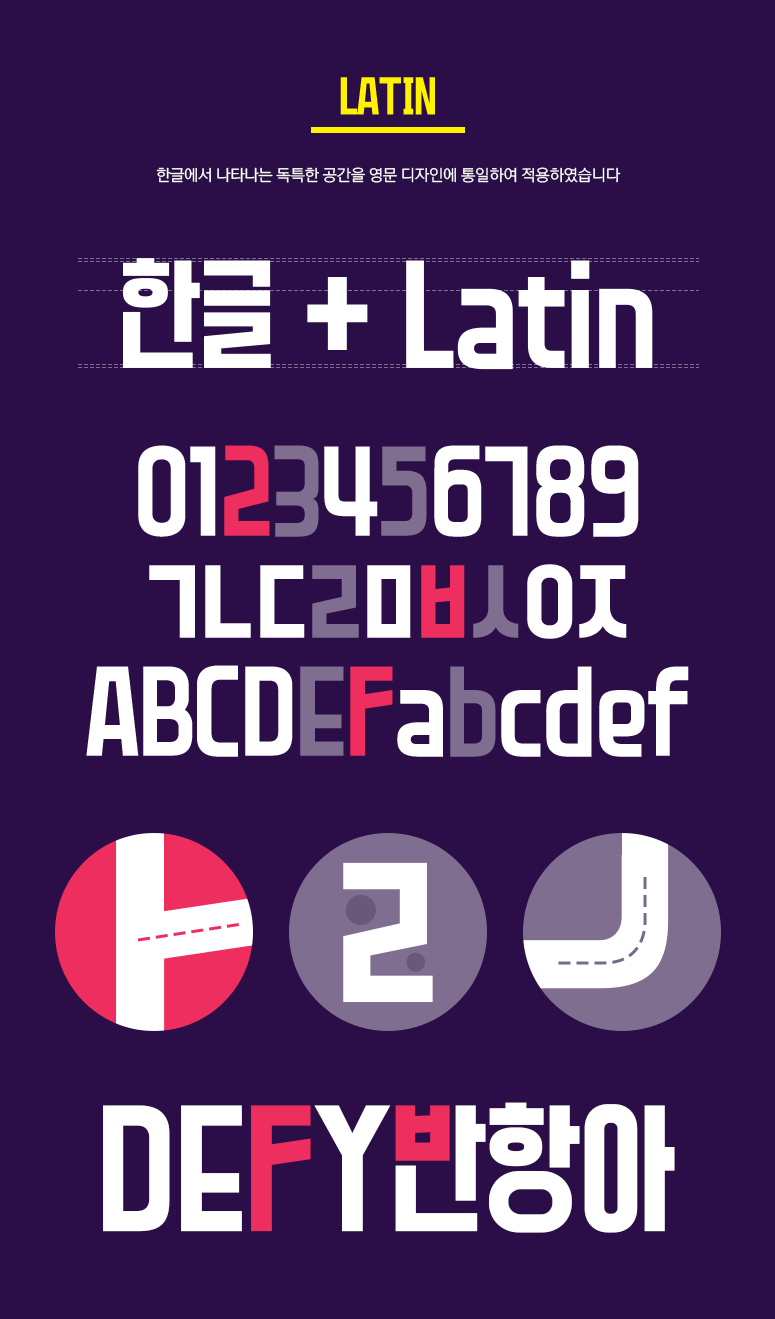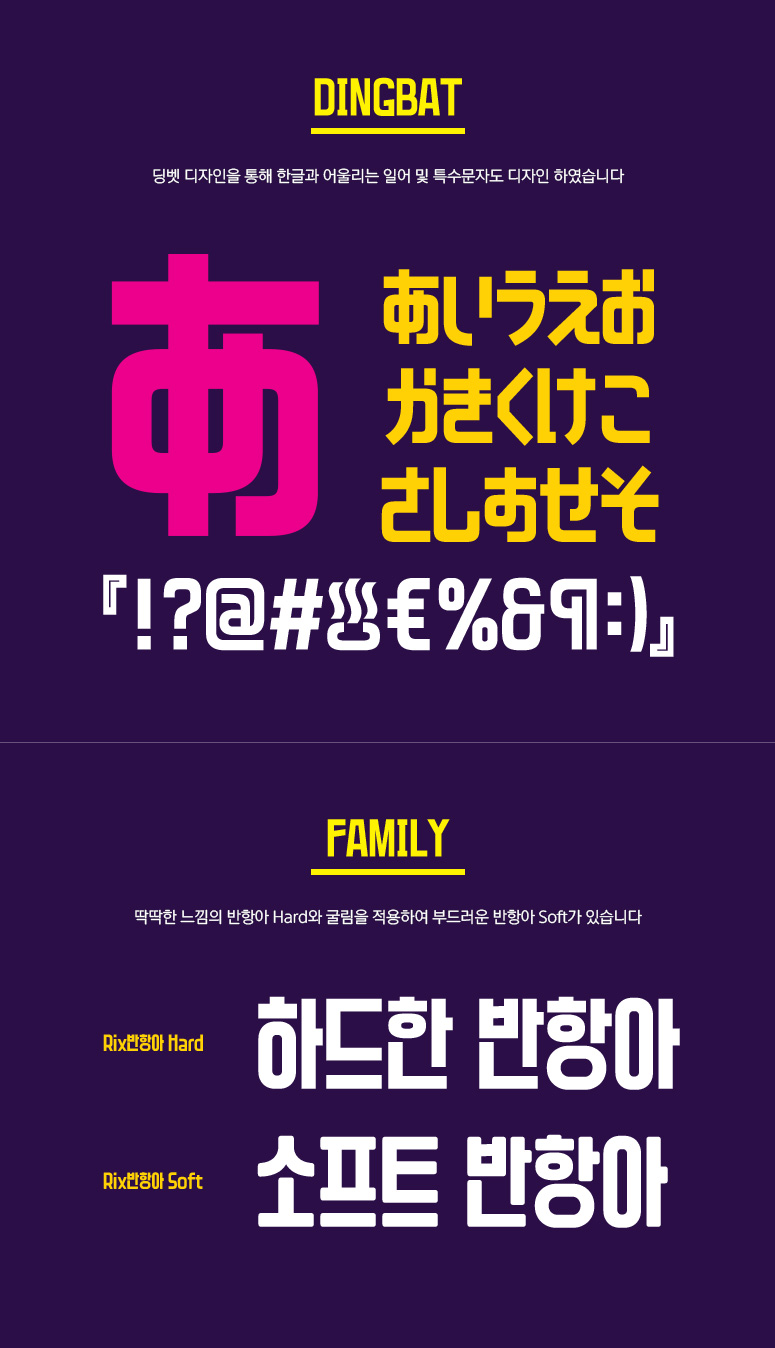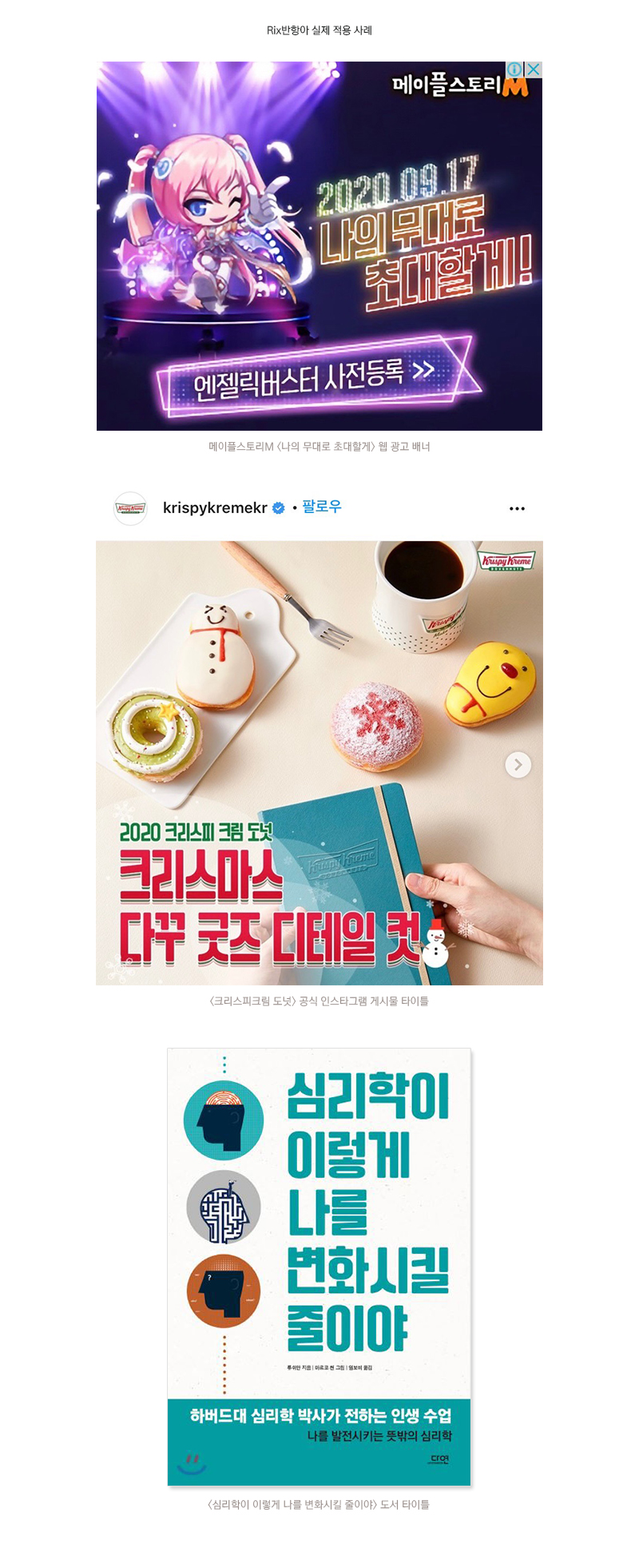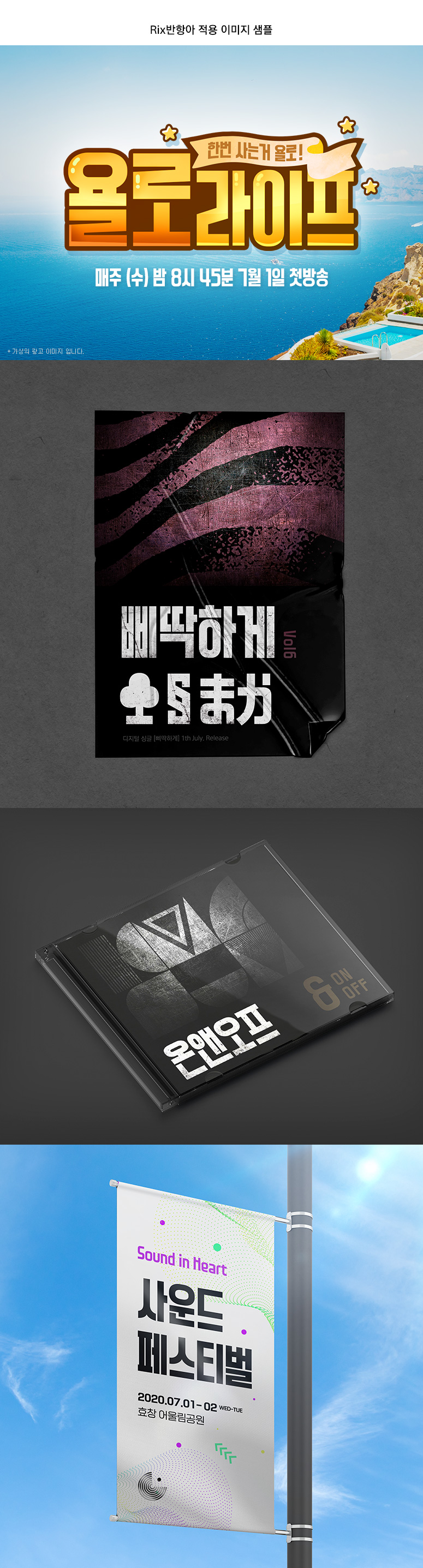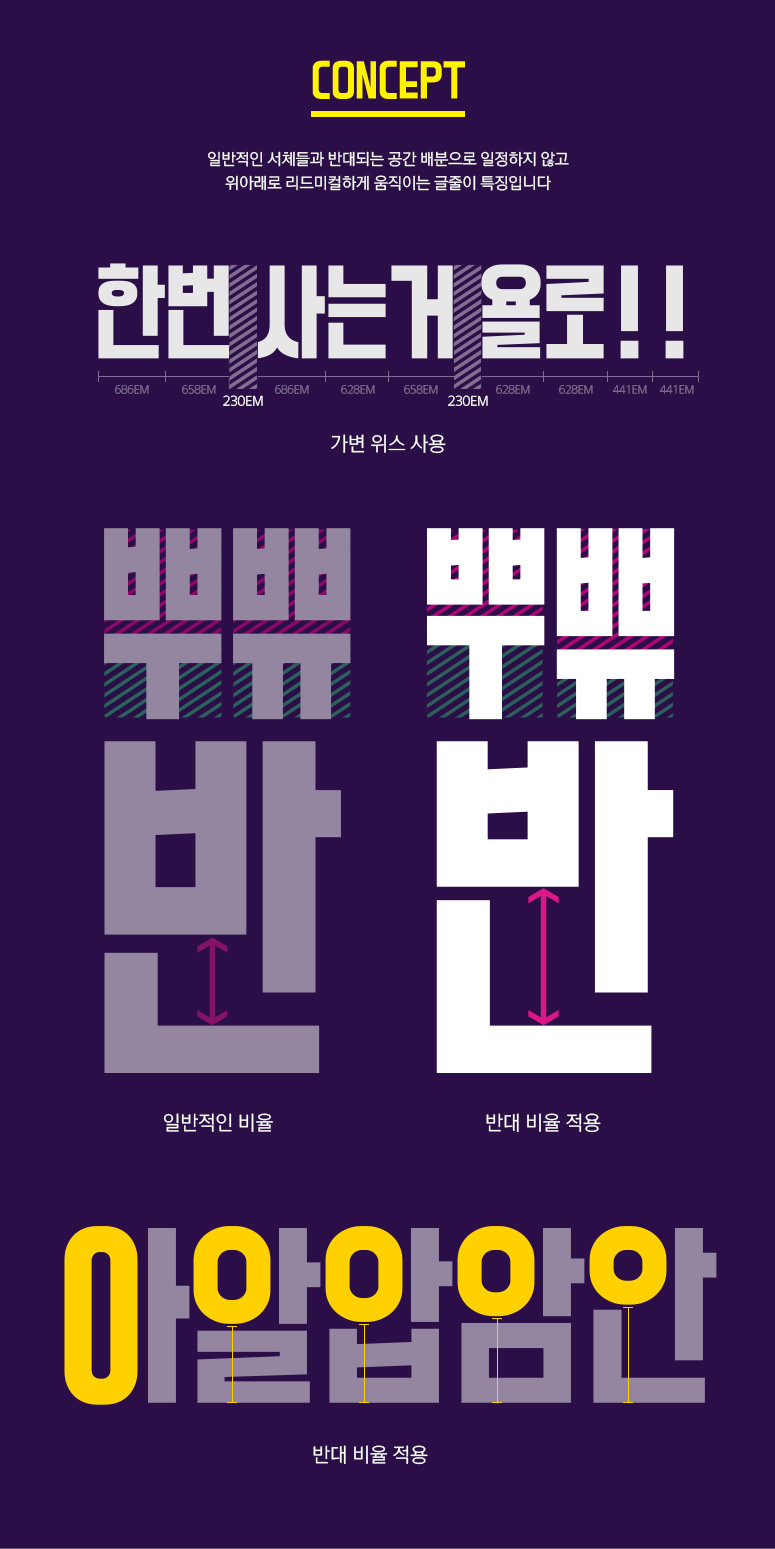
Rix반항아
2 종 - Hard, Soft
일반적인 서체들과 반대되는 공간 배분으로, 일정하지 않고 위아래로 리드미컬하게 움직이는 글줄이 특징입니다.
꽉 찬 모듈과 디테일한 굵기가 강한 임팩트를 전달하며, 모듈 안에서의 움직임을 통해 재미요소를 더한 서체입니다.
폰트명 Rix반항아 / RixDefyKid
폰트디자인 박윤상
디자인디렉팅 박용락